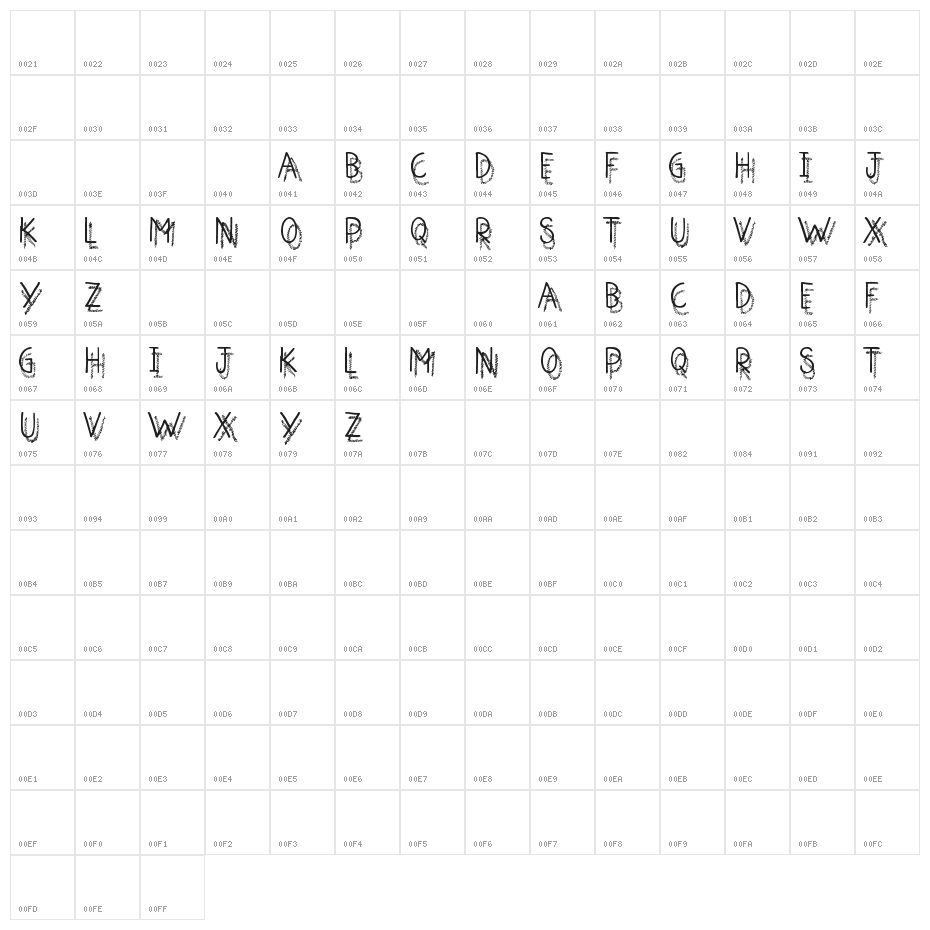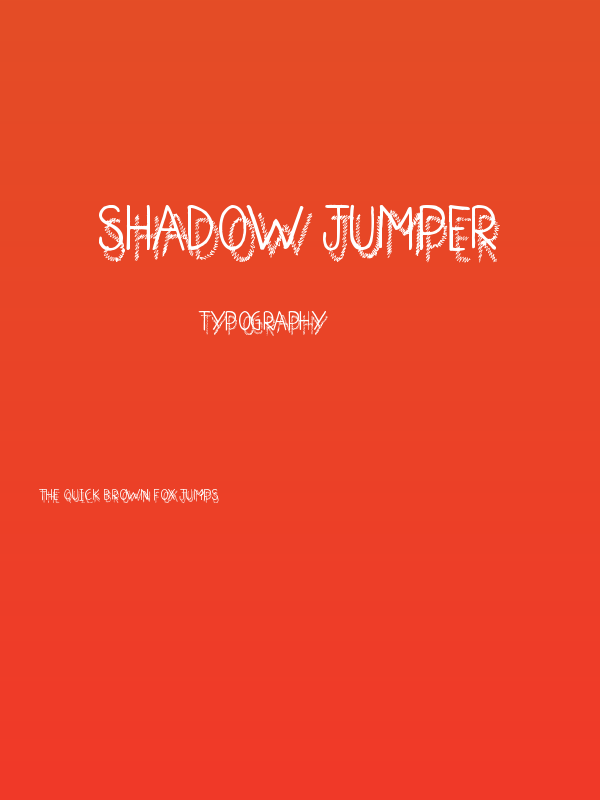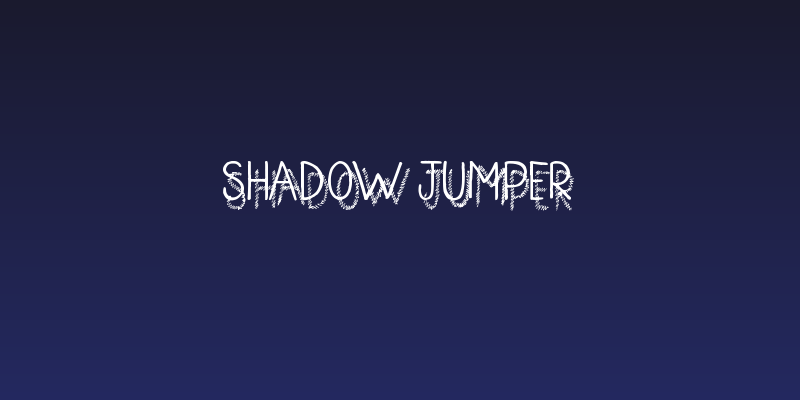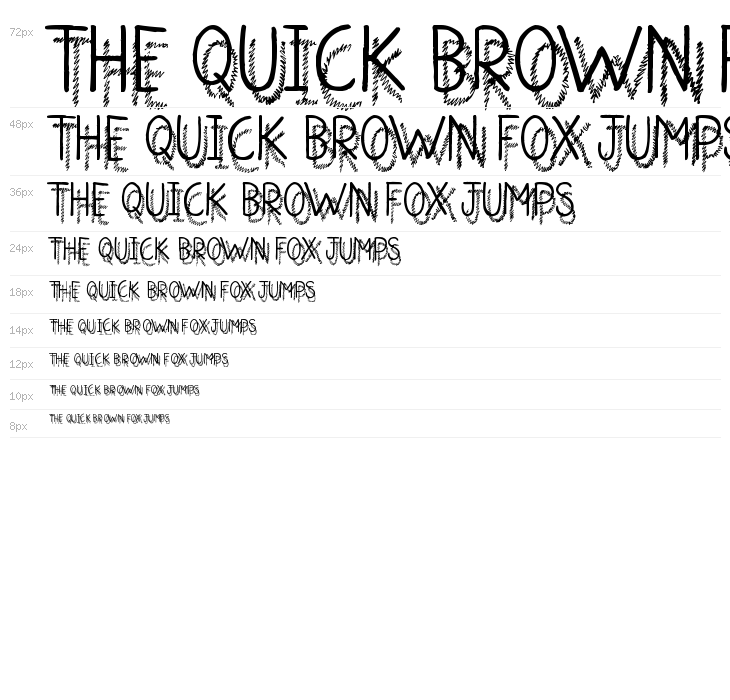
Shadow Jumper Font
| Estilo general | Playful, Energetic |
| Proyectos propuestos | Ideal for posters, comic book titles, children's book covers, and playful branding. |